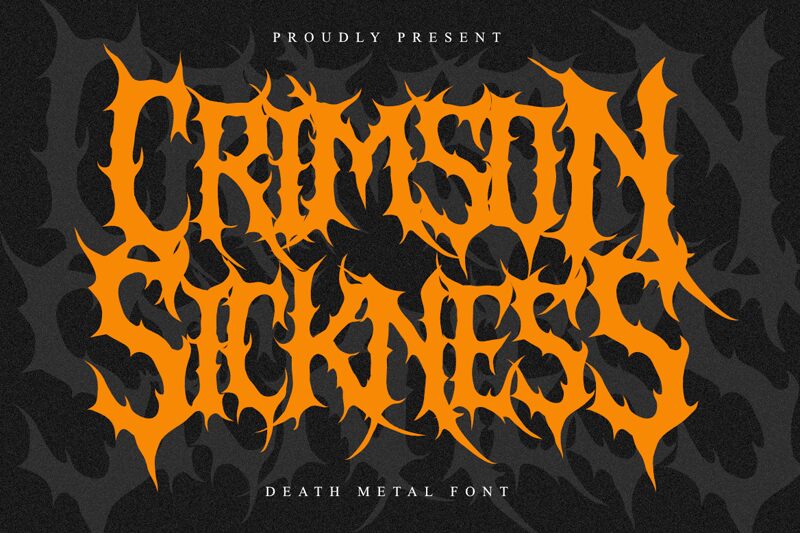
Crimson Sickness
Crimson Sickness de Masyafi Studio est une police gothique gratuite aux traits acérés en forme d'épines et aux découpes pointues, conférant à chaque lettre un aspect ciselé et dentelé. Les formes sont denses et anguleuses, avec des extrémités piquantes et des jonctions étroites créant une texture sombre et brute sur l'ensemble du mot.
Crimson Sickness est idéale pour les affiches d'horreur, l'identité visuelle de groupes de métal, les titres de jeux vidéo, les logos de salons de tatouage et les graphismes d'Halloween, car ses formes fracturées dégagent une énergie sauvage. Cette police gratuite convient également aux couvertures, aux designs de merchandising et aux titres éditoriaux lorsque vous recherchez un rendu à la fois agressif et ornemental.